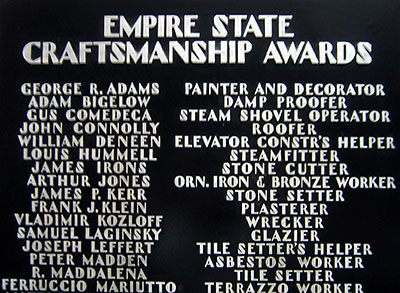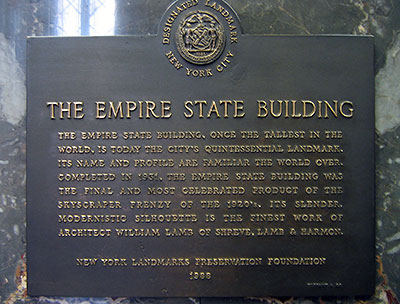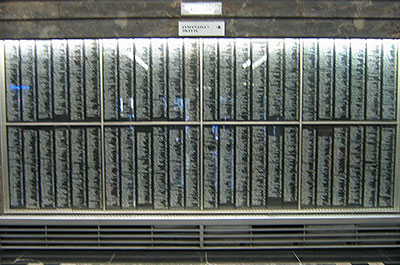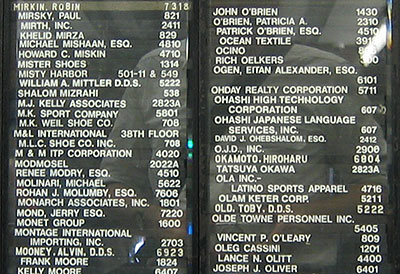
Empire State TypographyDas Empire State Building (*1931) ist seit dem Anschlag auf das
World Trade Center (1977 – 2001) wieder das höchste
Gebäude New Yorks. Der Besucherandrang ist enorm. Eine Stunde Wartezeit
muss man schon einkalkulieren, bevor man mit einem der 74 Aufzüge die
Aussichtsplattform ansteuern kann (15 $). Umsonst und sofort kann man die
Jahrzehnte alte Typografie des Gebäudes im Erdgeschoss
studieren.
![]() Architekten-Tafel am Empfang des Empire State Buildings im Erdgeschoss ![]() Beeindruckender Empfangsschalter, mit imponierender Metallbeschriftung aus der Jugendstilzeit Ein Wort zum Marmor des Empire State Buildings: Er stammt aus Deutschland, genauer aus Villmar an der Lahn. Angeblich haben die Architekten der monumentalen Innenausstattung Experten nach Europa geschickt, um in Italien, Frankreich und Deutschland verschiedene Marmorarten in Augenschein zu nehmen. Der Lahnmarmor wurde als besonders druckfest und wasserabweisend begutachtet und bekam den Zuschlag. Mehr dazu ... ![]() Gedenktafel aus Metall für die besten Handwerker ihrer Zeit ... Steinmetze, Dachdecker, Glaser, Pflasterer, Maler, Verputzer, ... ![]() Seit 1988 steht das Empire State Building unter Denkmalschutz ![]() An den beiden Eingängen stehen gigantische Tafeln mit den Mietern: 30.000 Menschen leben und arbeiten im Empire State Building, eine ganze Stadt in einem Gebäude ![]() Ausschnitt aus der 24-spaltigen »Klingelschildtafel« Herausgegeben: Mi - Juli 20, 2005 at 04:29 vorm. | |